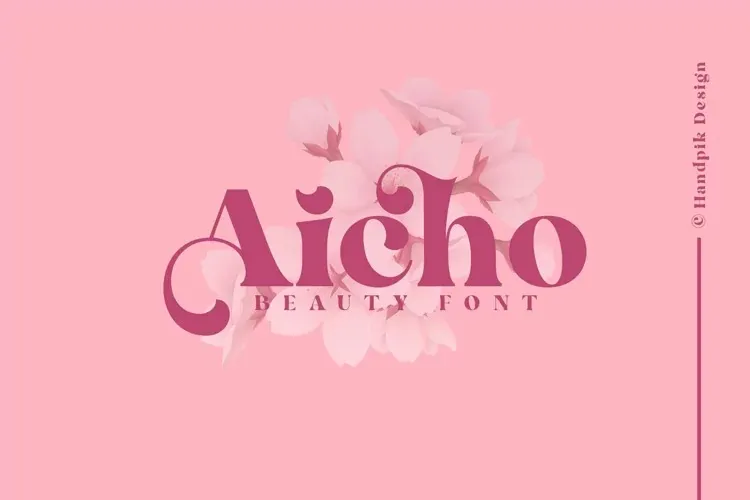
A Aicho Font é uma elegante serif que se destacou na criação do designer handpik através de sua personalidade única e seu toque fashionista. Com tons de caracteres alternativos infinitos e ligações únicas, ela se torna uma fonte versátil para múltiplas aplicações. Ideal para cards de convite, decorações, roupas, cartões de felicitações e outros. Além disso, a Aicho Font oferece letras maiúsculas e minúsculas, números, pontuação e suporte multilíngue, proporcionando uma gama variada de opções. Com sua gama de ligaturas e alternativas estilizadas, ela se torna um recurso ideal para designers que buscam personalidade em suas criações.